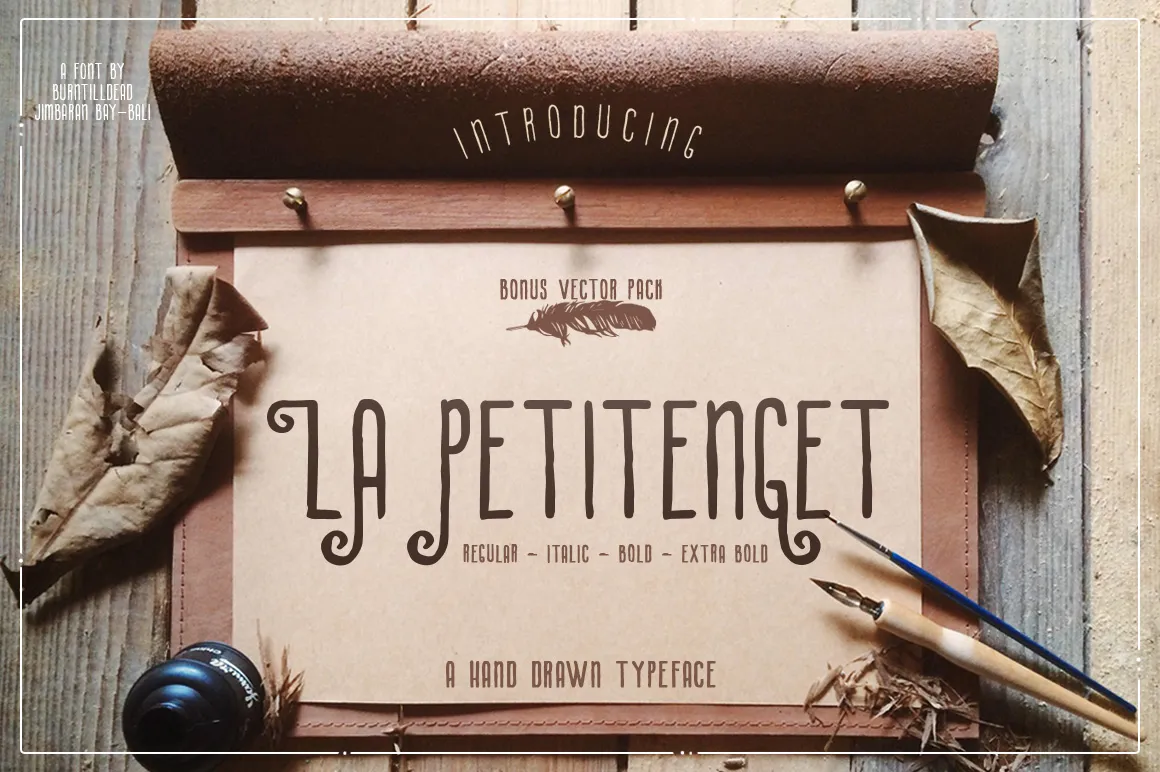
La Petitenget Font
La Petitenget é uma fonte Blackletter que garante seu texto destacar-se de forma elegante e sofisticada. Perfeita para aplicação em menus, lojas de surfe, etiquetas de mercado livre, sacolas de shopping e qualquer ideia imaginativa que você possa ter. Esta fonte oferece alternativas entre letras maiúsculas e minúsculas, garantindo uma versatilidade imensa. Ela também suporta várias línguas internacionais. Para ver todos os elementos da fonte, basta clicar no segundo visualizador de pré-visualização. La Petitenget é perfeita para quem busca um toque único e moderno em seus projetos gráficos.